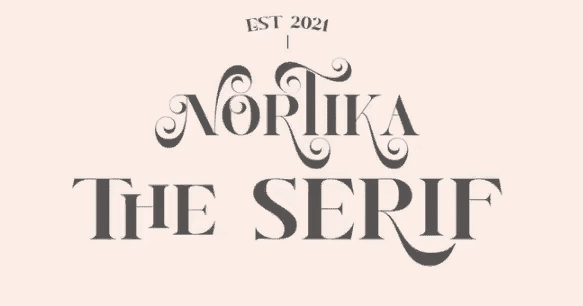
Название: Nortika Font (2021)
Nortika - стильный и выразительный шрифт с засечками. Смело добавляйте его в свои любимые творения и позвольте себе поразиться полученному результату. Этот шрифт закодирован в PUA, что означает, что вы можете легко получить доступ ко всем глифам и штрихам!
Nortika также включает в себя полный набор:
прописные и строчные буквы
Многоязычные символы
Цифры
Пунктуация
Стандартные лигатуры
Дискретные лигатуры
Альтернативы